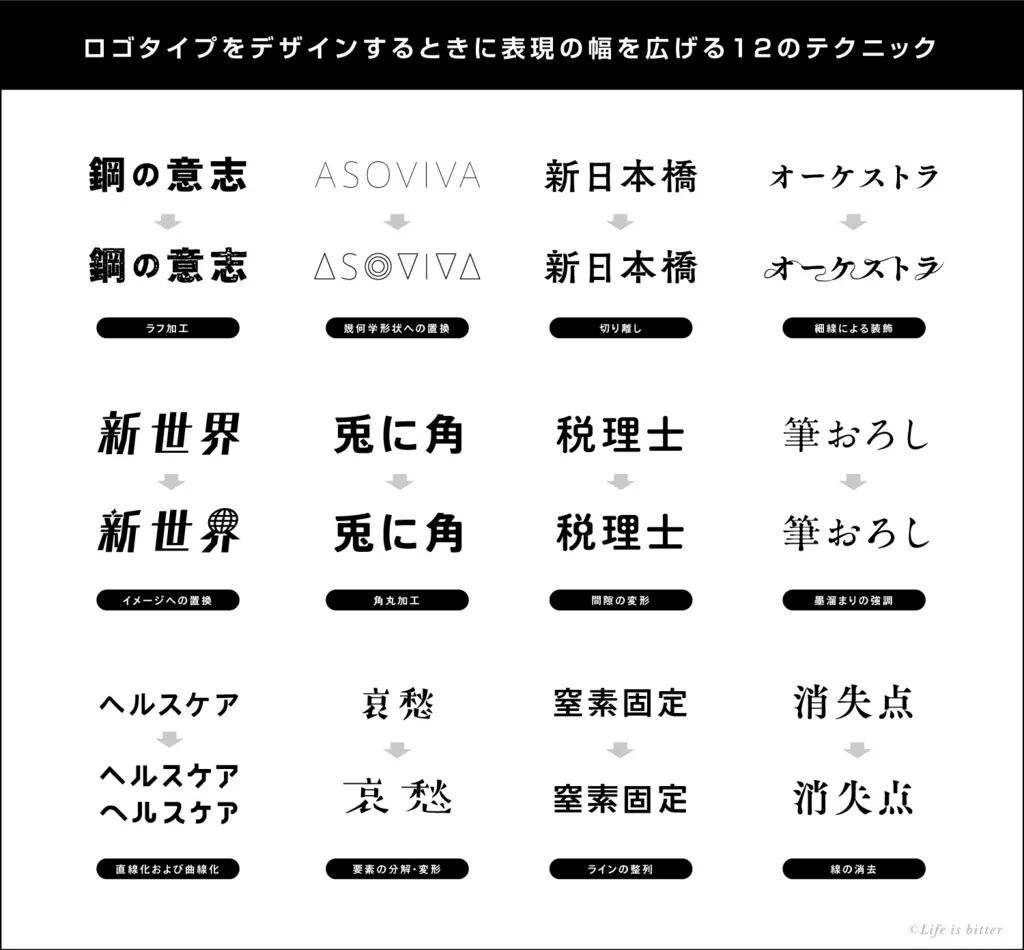
字体设计有什么技巧?
字体在VI / CI的制定和品牌推广中发挥字如着极其重要的作用。向客户提案时,应该通过反复试验来展开创意,以达到目标式。
日本设计师 カワラ 非常喜欢字体设计,这次,他总结了字体设计时经常尝试的方法,并分析了各种字体以及可以分解的技巧。希望它对于那些对字体制作感到困惑的人有所帮助。